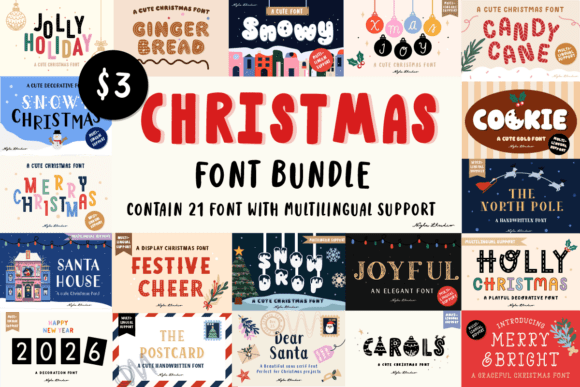
Christmas Font Bundle
Mencari elemen reka bentuk yang sesuai boleh menjadi mencabar, tetapi Christmas Font Bundle menawarkan koleksi luar biasa yang menaik taraf karya anda serta-merta.
Sama ada anda mencipta produk POD (Print on Demand), jemputan perkahwinan atau grafik media sosial, Christmas Font Bundle amat bersesuaian.